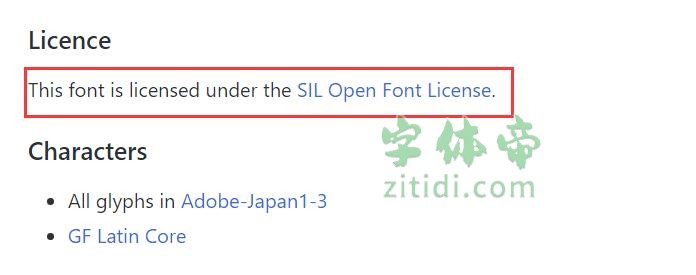
枯枝火柴体字体信息
日本著名字体设计公司Fontworks免费开源一款字体,是原始的流行风格字体。顾名思义,它是一种带有可爱调皮的气氛的字体,其设计像笔杆一样以直线表示。此外,由于它可以表达田园诗般的气氛,因此它是一种可广泛用于纸张媒体和数字内容的字体。
“枯枝火柴体”是一款书写很新颖的字体,字体大方,适合各种设计作品使用!欢迎下载!